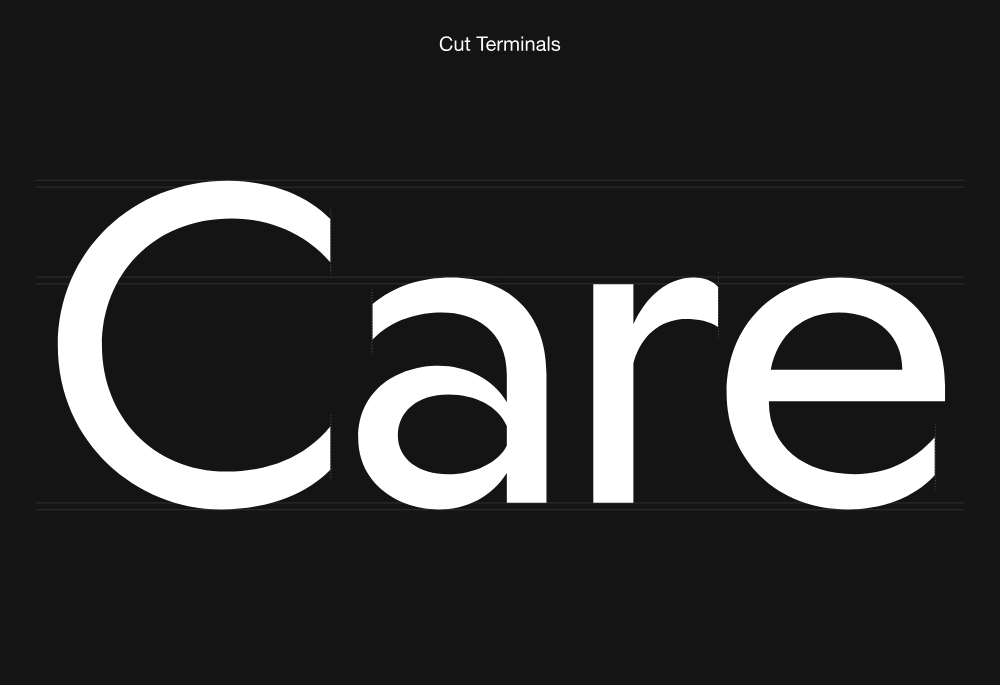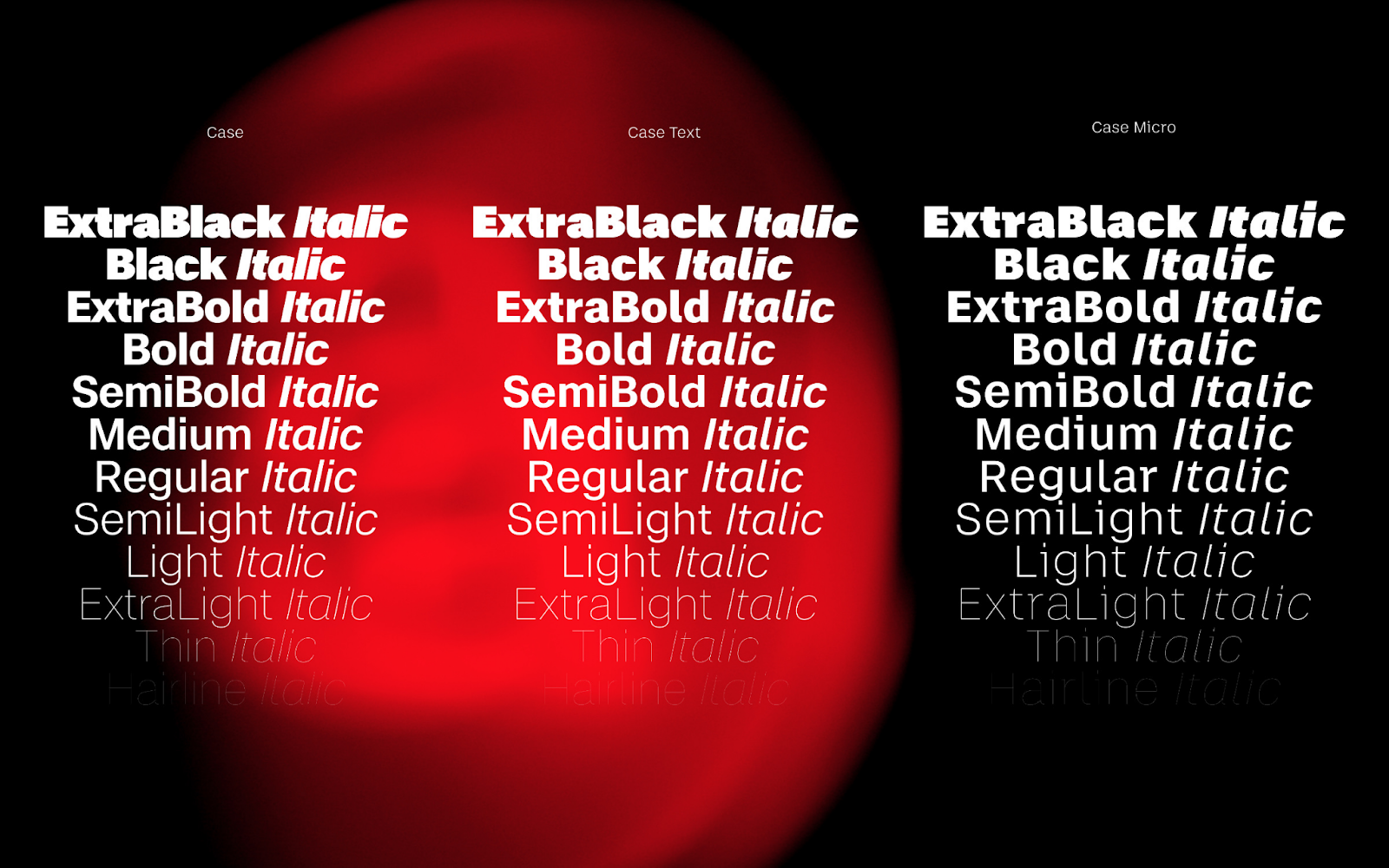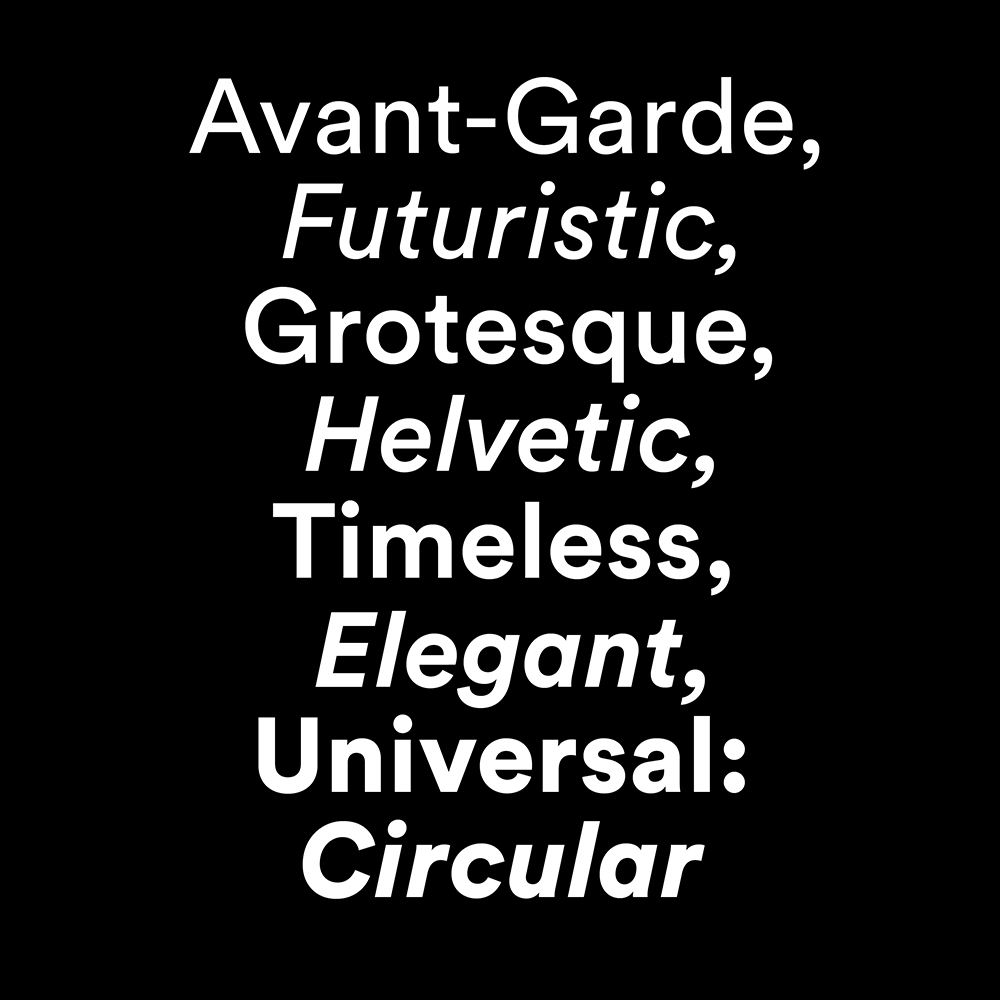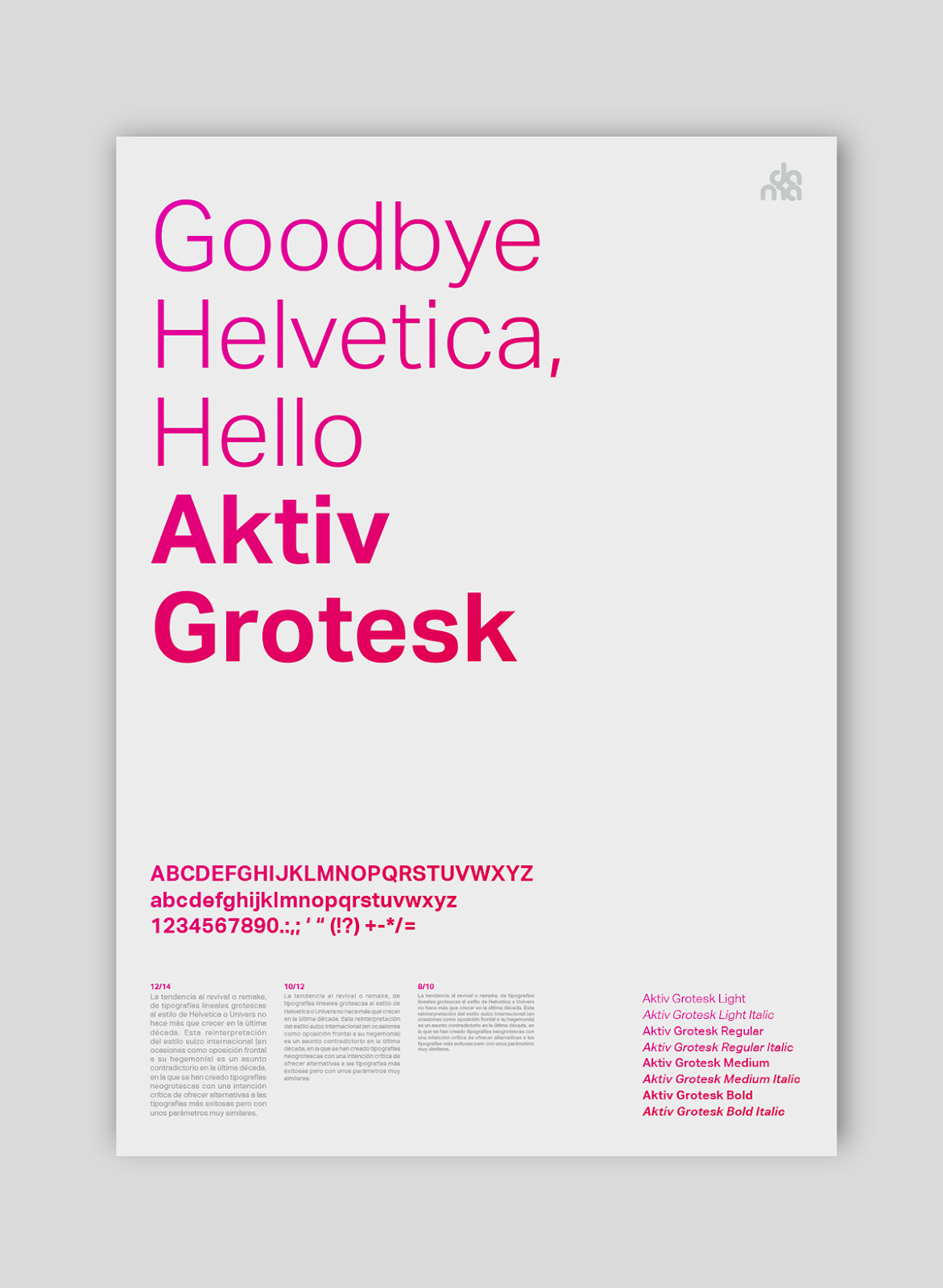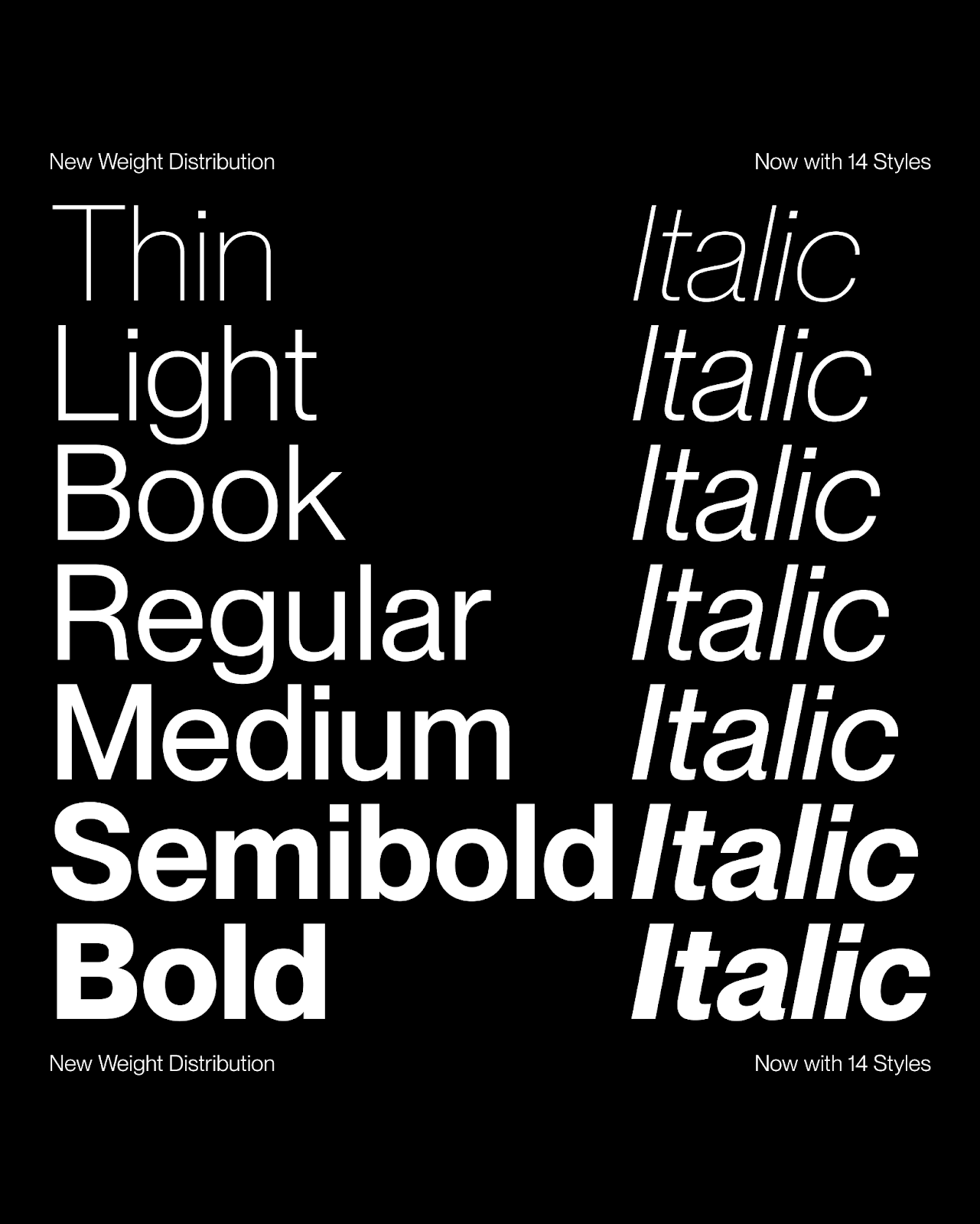
Xu hướng font chữ mỗi năm lại không ngừng thay đổi nhằm theo kịp và đáp ứng được thị hiếu. Bài viết này tổng hợp 50 font chữ tuyệt vời hứa hẹn sẽ trở nên phổ biến trong năm 2024 Designer không nên bỏ lỡ.
Font chữ là một thành tố quan trọng trong quá trình thiết kế bất kì ấn phẩm hoàn chỉnh nào. Một font chữ phù hợp và thu hút có khả năng nâng tầm sản phẩm của bạn. Hiện nay, có vô vàn các font chữ khác nhau được tạo ra để đáp ứng nhu cầu đa dạng của thị hiếu.
Để giúp bạn cập nhật xu hướng cũng như dễ dàng tìm kiếm kiểu chữ phù hợp cho dự án của mình, trong bài viết này, Arena Multimedia sẽ mang đến cho bạn list 50 font chữ hiện đại và thời thượng, hứa hẹn sẽ được các Designer ưa chuộng năm 2024!
Font chữ không chân (Sans Serif)
1. Neue Montreal của Pangram Pangram
Được thiết kế bởi Mat Desjardins, Neue Montreal là một font chữ Grotesque đa năng mang tinh thần của một font chữ Display (font chữ hiển thị). Do được lấy cảm hứng từ cảnh vật tại Montreal, font chữ này đã được rất nhiều thương hiệu địa phương ưu ái đón nhận. Đặc biệt, đội bóng thành phố Montreal đã sử dụng font chữ này trong quá trình tái định vị thương hiệu gần đây.
Neue Montreal có 14 trọng lượng gồm bảy chữ đứng và bảy chữ nghiêng. Bên cạnh đó, bộ font này có cả chức năng điều chỉnh khoảng cách giữa các ký tự gần nhau hơn và chức năng hỗ trợ cho hệ thống chữ viết sử dụng cho nhiều ngôn ngữ ở lục địa Á-Âu (Cyrillic).
2. Aktiv Grotesk của Dalton Maag
Aktiv Grotesk là kiểu chữ Grotesque Sans được mô tả như một “sát thủ “diệt” Helvetica”. Bộ font đi kèm với kiểu chữ Weight, Width và Italic, hỗ trợ mười hệ thống viết toàn cầu và sở hữu một bộ biểu tượng vô cùng phong phú. Được hoàn thiện bởi công sức của 16 nhà thiết kế chữ có kinh nghiệm, font chữ này được coi là một “cường quốc” của tính linh hoạt và đa dạng chức năng.
3. Degular của OhNo Type
Trong khi hầu hết các font chữ trong danh sách đều có đặc điểm thu hút sự chú ý, font chữ Degular lại muốn “hòa tan” vào background với tinh thần của một cỗ máy tạo nhiễu trắng mang phong cách Nhật Bản. Được thiết kế bởi James Edmondson, Degular gồm có bảy trọng lượng, ba kích thước với hai dạng chữ La-tinh và in nghiêng.
4. Case của Fontwerk
Kiểu chữ Neo-Grotesque này là một lựa chọn mới mẻ thay thế cho các kiểu chữ cổ điển có phần “cũ kỹ”. Các nhà thiết kế chữ Erik Spiekermann, Anja Meiners và Ralph du Carrois đã phân tích lại nó từ đầu và dựa vào đó để phát triển thêm, giúp nó trở nên linh hoạt hơn khi ứng dụng trong các dự án branding phức tạp, đồng thời tăng gấp đôi số lượng font và ký tự.
5. Circular của Lineto
LL Circular mang đến một cái nhìn mới mẻ về thể loại Grotesque hình học. Nó kết hợp nhuần nhuyễn sự thuần khiết với sự ấm áp. Đồng thời, nó tạo ra sự cân bằng giữa chức năng, sự chặt chẽ về mặt khái niệm, tay nghề và phong cách riêng. Với đặc tính riêng biệt và sức hấp dẫn gần như đối với tất cả mọi người, font chữ tuyệt vời này đi kèm với tám trọng lượng và là sự lựa chọn lí tưởng cho ngữ cảnh biên tập, quảng cáo hoặc branding. Nó đặc biệt phù hợp cho tiêu đề hoặc phần nội dung chính.
6. Roobert của Displaay
Font chữ Roobert ban đầu được Displaay và Anymade Studio phối hợp thiết kế nhằm tạo ra một kiểu chữ độc quyền dành riêng cho Moogfest 2017 – một lễ hội âm nhạc và công nghệ tại Bắc Carolina tôn vinh kỹ sư Robert Moog. Phông chữ sans-serif hình học này được lấy cảm hứng từ biểu tượng Moog.
7. Strawford của Atipo Foundry
Strawford là một kiểu chữ Sans Neo-geometric với độ tương phản thấp, chiều rộng cân đối và chiều cao cơ bản của một dòng chữ thấp. Tất thảy tạo nên một diện mạo đơn giản và gọn gàng. Bộ chữ này gồm bảy độ dày khác nhau cùng với kiểu chữ in nghiêng.
Đặc trưng của Strawford chính là rất dễ nhận biết và dễ đọc. Với đặc tính như vậy, Strawford trở thành một lựa chọn rất phù hợp cho thiết kế UI/UX, thiết kế ứng dụng, xây dựng thương hiệu, tạo logo, quảng cáo hoặc thiết kế bao bì sản phẩm.
8. Agrandir của Pangram Pangram
Kiểu chữ sans-serif đương đại này được “sinh ra” với vai trò như một một phương pháp đối trọng với các font chữ hiện đại trung tính. Không căn chỉnh, kỳ quặc và vui nhộn, bộ font này bao gồm 74 font (bảy trọng lượng, năm độ rộng, in nghiêng và bốn kiểu văn bản). Ngoài ra, nó còn có một font có thể biến đổi ba trục.
9. Sonic của F37 Foundry
F37 Sonic là một kiểu chữ sans serif hình học thú vị. Nó sắc nét, ấn tượng và dễ dàng thu hút sự chú ý. Hình dáng tròn của nó bắt nguồn từ các khoảng trống nằm trong một kí tự của các dạng chữ chứ không phải bên ngoài – điều vốn phổ biến hơn. Điều này tạo ra một cấu trúc đặc biệt trên trang với sự đối lập của các chữ cái hẹp, thẳng (như n, t và f) và các chữ cái chéo, tròn rộng (như o, a và v).
10. Noi Grotesk của Fiexen Fonts
Được thiết kế bởi Robin Eberwein và Felix Pfäffli, Noi Grotesk là một kiểu chữ sans-serif hiện đại mang đến một cảm giác vui tươi. Bộ chữ này bao gồm 16 font với tám trọng lượng và một trong hai phiên bản font có thể biến đổi. Đặc biệt, nó được tối ưu hóa cho cả in ấn và website.
Nguồn ảnh: Proof&Co.
11. At Haüss của Arillatype Studio
At Haüss là một sự tái hiện đương đại của các font chữ neo-grotesque giữa thế kỷ 20. Sự kết hợp này tạo ra một kiểu chữ thuần khiết và thanh lịch với cấu trúc chắc chắn và cân đối. Nó bao gồm 20 kiểu dáng, bắt đầu với trọng lượng Air tinh tế, đi qua Retina được tối ưu hóa cho màn hình có mật độ cao và cuối cùng đến với Super mạnh mẽ. Nó cũng sở hữu dạng một font biến đổi với hai trục: Trọng lượng [Air–Super] và Nghiêng [0°–10°].
Nguồn ảnh: Arillatype.Studio®
12. Gustavo của Lift Type
Được thiết kế bởi Romain Oudin năm 2018, Gustavo là một kiểu chữ sans-serif hình học, gây ấn tượng với đặc điểm rộng theo chiều ngang. Đây cũng là một kiểu chữ vừa cổ điển lại vừa cá tính. Hệ thống kiểu chữ đầy đủ của Gustavo bao gồm năm trọng lượng, một phiên bản nghiêng và một bộ biểu tượng đa dạng.
Nguồn ảnh: Lift Type
13. Ritma của British Standard Type
Ritma là một kiểu chữ sans-serif humanist đương đại. Bộ font kết hợp chiều rộng của kiểu chữ humanist, chiều cao cơ bản của một dòng chữ cân đối và hình dáng rộng một cách tinh tế và hiện đại. Đặc biệt, bộ font này rất thực tế, nhiều chức năng biểu cảm và có nhiều bộ ký tự phong cách, bao gồm cả các ký tự trong sách giáo khoa và các tính năng OpenType.
Nguồn ảnh: British Standard Type
14. Dwight của Lift Type
Dwight là một kiểu chữ sans-serif hình học có phần cứng nhắc nhưng cũng rất độc đáo. Với dấu chấm câu tròn rõ ràng, gợi nhớ đến những tờ giấy đục lỗ, bộ font là một lựa chọn tuyệt vời cho văn bản và tiêu đề. Hệ thống kiểu chữ đầy đủ của Dwight có sẵn bảy trọng lượng, bao gồm phiên bản nghiêng, một bộ ký tự liên kết, một số ký tự thay thế và một loạt các biểu tượng.
Nguồn ảnh: X.com
15. Lay Grotesk của Colophon
Lay Grotesk là kiểu chữ sans-serif đương đại tái hiện kiểu dáng của các font cổ điển như Helvetica, Neue Haas Grotesk và Folio. Font chữ này được thiết kế theo phong cách trung lập kiểu Thụy Sĩ nhưng “làm dịu đi” sự cứng nhắc của chúng. Tất thảy tạo nên một sự đối lập rõ ràng hơn và làm mềm mại các hình khối, khiến cho kiểu chữ trở nên thanh lịch đồng thời không kiểu cách, rườm rà.